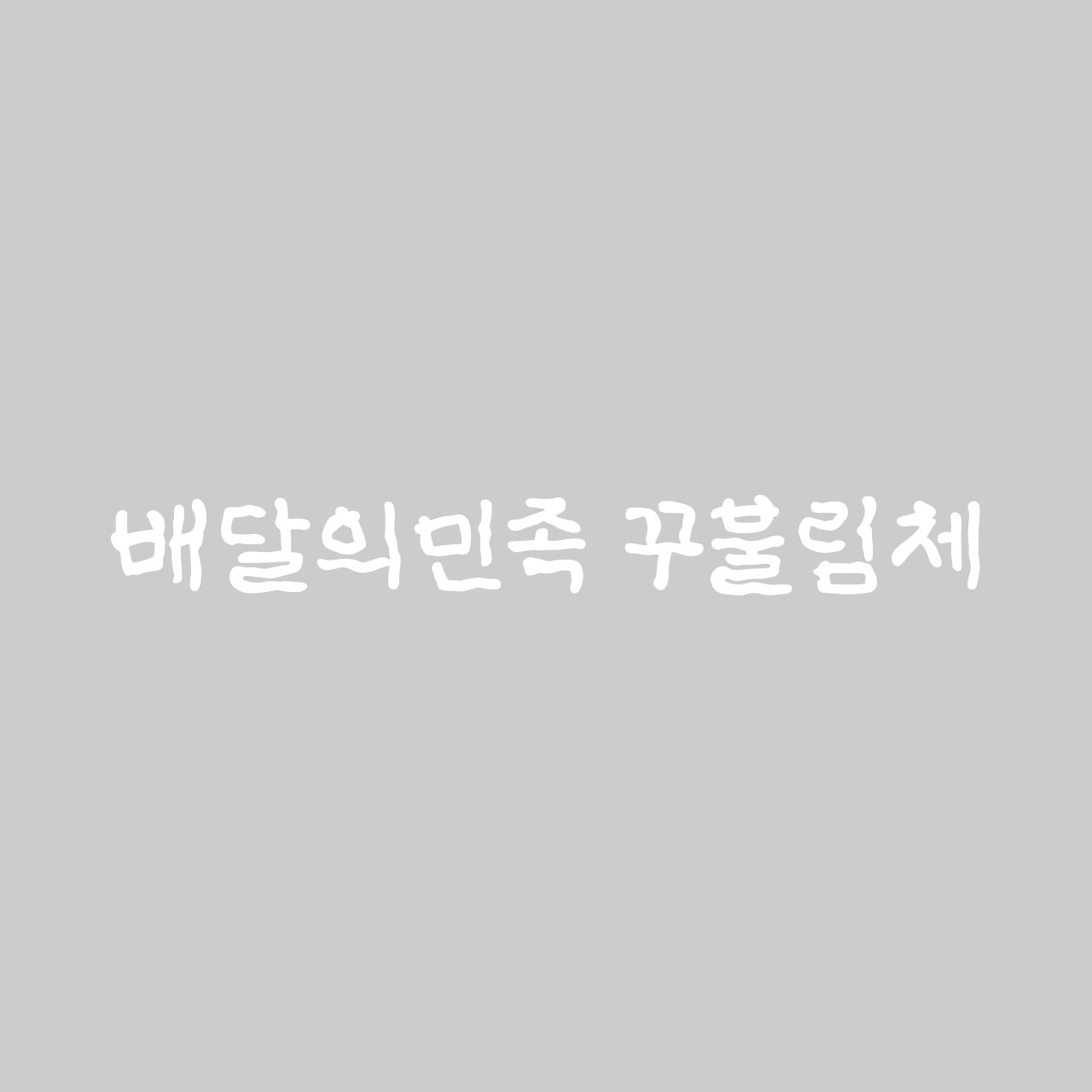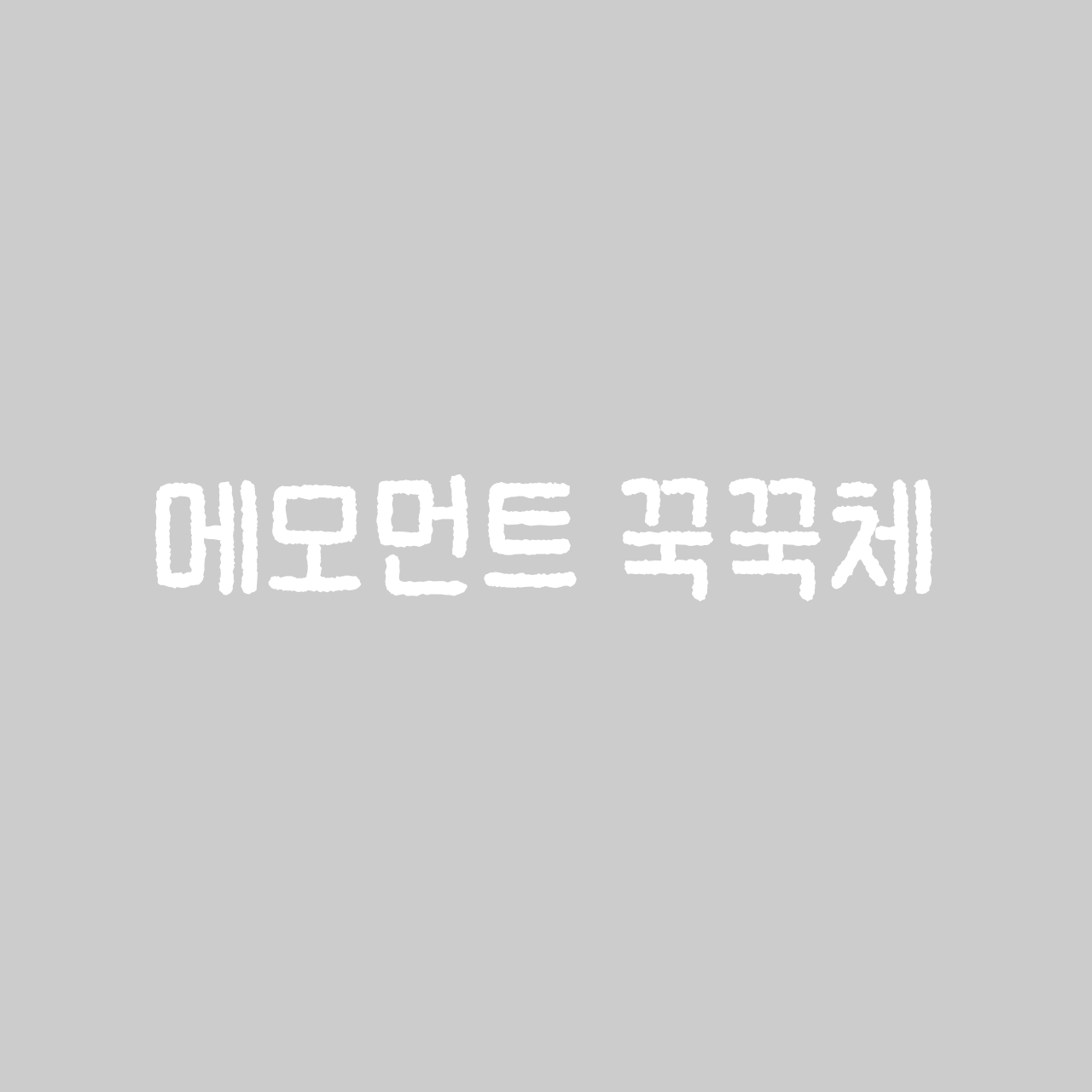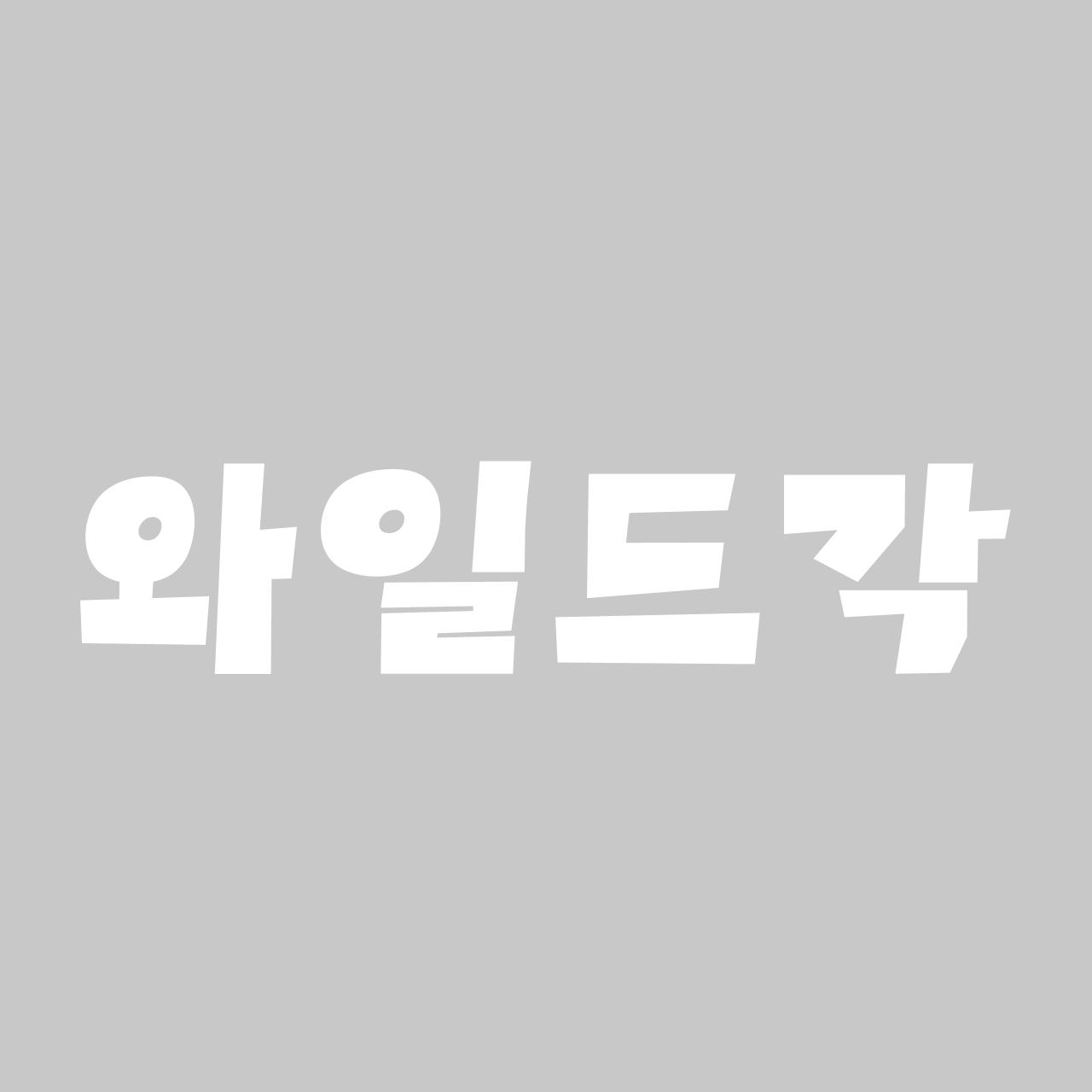
우리에게 릴스와 쇼츠 같은 숏폼 콘텐츠는 이제 일상의 한 부분이 되었습니다. 스크롤을 내리다 보면 "이 글씨체 뭐지?" 하고 한 번쯤 궁금했던 폰트도 많으셨을 텐데요.
그래서 준비했습니다. 지나가다 한 번쯤 눈길이 갔던, 그리고 내 콘텐츠에도 한 번쯤 써보고 싶은 폰트들을 소개합니다.
#01. 질감이 살아있는 손글씨
릴스에서는 친근한 분위기를 전하기 위해 손글씨 스타일의 폰트가 많이 활용됩니다. 오늘 소개해 드릴 폰트는 특유의 독특한 질감이 자연스럽게 시선을 끄는 것이 특징인데요. 영상 상단의 제목이나 한 줄 포인트 문구에 특히 잘 어울리고, 긴 문장에서도 생각보다 잘 눈에 들어옵니다.
• 좀 더 개성 있고 시선을 확 끌고 싶다면? 「배달의민족 꾸불림체」
• 단정하면서도 따뜻한 감성을 담고 싶다면? 「메모먼트 꾹꾹체」
#02. 사각사각 오려낸 듯한 폰트
이 폰트, 분명 어디선가 한 번쯤은 보셨을 것 같은데요. 종이를 오려 붙인 듯한 형태와 다양한 각도가 만들어내는 경쾌한 리듬감이 포인트입니다. 한눈에 시선을 사로잡는 개성이 있어 제목이나 썸네일처럼 첫인상이 중요한 곳에 특히 잘 어울리죠.
• 거칠고 자유로운 분위기를 원한다면? 「와일드각」
• 귀엽고 오밀조밀한 느낌이 취향이라면? 「Ok단단체」
#03. 오히려 기본 미감이 대세
요즘 릴스를 보면 화려한 폰트보다 우리에게 익숙한 기본 서체 느낌의 폰트를 사용하는 경우도 정말 많습니다. 꾸미지 않은 듯한 담백함이 오히려 더 세련되고 트렌디한 분위기를 만들어주죠.
여기서 한 가지 꿀팁! 폰트에 살짝 기울임(Italic) 효과를 더해주면 훨씬 감각적이고 힙한 느낌을 연출할 수 있습니다.
• 레트로한 윈도우 감성을 찾는다면? 「조선굴림체」
• 어딘가 문학적인 느낌을 원한다면? 「부크크 명조」